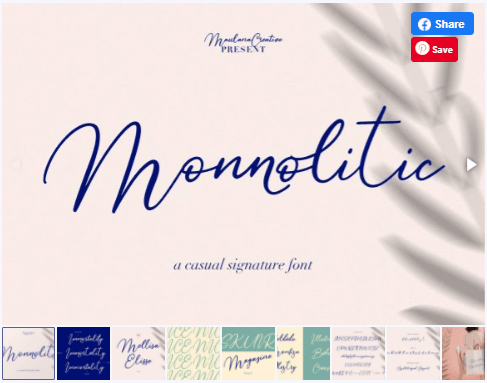
Monnolitic Font
Monnolitic - это плавный и изысканный рукописный шрифт. Он сохраняет свои классические каллиграфические мотивы, но при этом выглядит современным и свежим. Полюбите его и доведите свои проекты до высочайшего уровня!